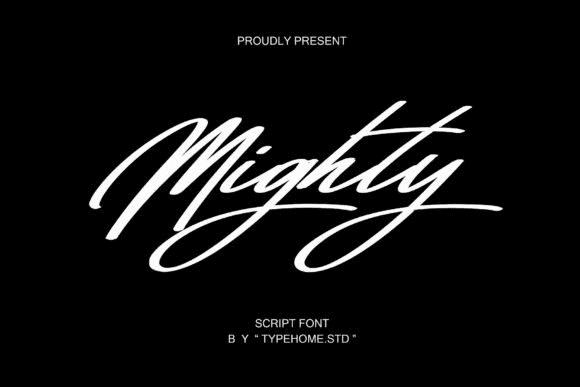
Название: Mighty Font (2021)
Mighty Script - это плавный, элегантный и адаптируемый шрифт.
Этот универсальный шрифт имеет широкий спектр применения - от поздравительных открыток до заголовков - и гарантированно придаст романтическую атмосферу вашему следующему проекту.